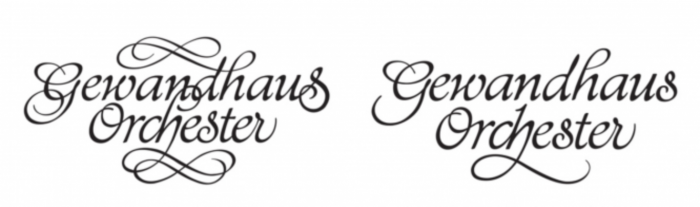
Gewandhausorchester: Logo-Redesign
... kannst du Beispiele der Fehler nennen?
ja freilich.
Aber ich bin überzeugt, daß nicht nur ich das kann. Das kann jeder, der etwas Ahnung von Schrift od. Kalligraphie hat. Es geht hier nicht um mich sondern um die Qualität einer wichtigen Arbeit. Deswegen jetzt hier ein etwas verwegener Vorschlag.
– Wer etwas konkretes zu dieser Kritik beisteuern möchte, lade die angehangene Datei herunter und drucke sie mit 100% auf A4 aus.
– mit Bleistift od. Farbstiften darauf die kritisierten Stellen markieren und benennen.
– den Kritikbogen dann fotografieren od. einscannen.
Dann wäre ein Vergleich der versch. Kritiken hier vermutlich sehr aufschlußreich. Das funktioniert aber nur, wenn wir uns auf einen gemeinsamen Zeitpunkt der Veröffentlichung einigen, damit wäre garantiert, daß jeder unbeeinflußt von anderen Meinungen seine Einschätzung abgibt.
hmm. dann würde aber sicherlich ein komplett anderer schriftzug dabei herauskommen. ich habe das redesign so verstanden, das der bestehende schriftzug nur vereinfach werden sollte, oder sind diese fehler in dem original nicht vorhanden?
Ich meine mit der Kritik nicht die Entscheidung(en) zur Vereinfachung/Veränderung des Zeichens. Solche Dinge sind legitim und auch immer subjektiv bewertbar. Nein, ich meine die handwerkliche Ausführung der Reinzeichnung, so wie sie jetzt vorliegt. Als wenn man den Entwurf so aber richtig machen würde.
… eignet sich das Foto nicht eher zum Pixelzählen als zur Beurteilung von Linien?
die Auflösung ist ausreichend.
Interessante Diskussion.
Ich glaube, dass gute Gestaltungsprozesse dialogisch verlaufen, egal ob sie mit einer Person oder mit vielen Personen geführt werden. Wichtig ist, dass man als Fachmann vom Kunden ernst genommen wird. Was für den Kunden aus Sicht des Fachmanns auch gelten muss. Ich finde die Herangehensweise des Büros ganz gut, stärkt es doch die Zusammengehörigkeit des Orchesters von innen. Grafische Ansätze, wie so etwas ausehen kann, gibt es viele und keiner ist womöglich unbedingt schlecht. Aber die Demokratie wurde in der Frage des Schriftzuges nicht wirklich ernst genommen, so mein Eindruck.
Ich mache häufig die Erfahrung, wenn ich mit einem Kunden gut in Kontakt gekommen bin, dass selbst der Laie in der Lage ist, mir als Gestalter zu Detailfragen gute Rückmeldungen zu geben. Außerdem sollte man die Strategie dieses Briefings nicht mit der Überarbeitung dieses besonderen Schriftzuges vermischen.
Die Überarbeitung ist bei genauerem Hinsehen aber tatsächlich ein trauriger Rest von Tschörtners Vorlage. So etwas hätte die Agentur an einen Fachmann abgeben sollen. Natürlich kann man einen solchen Schriftzug auch vereinfachen, aber eben nur mit kalligrafischer Erfahrung.
Nur neben bei zum Aspekt »Life-Layouting« zwei weitere Stimmen.
Aus zuverlässiger Quelle habe ich vorgestern die Einschätzung gehört, daß die Orchestermitglieder »das nicht ernst genommen haben und sich verschaukelt fühlten«.
Gestern kommentierte eine Kalligraphie-Kollegin: »Ganz schlimm finde ich diese Bejubelung des Prinzips "Live-Layouting"! Ich bin geneigt, dies mit dem früheren sog. Klofrauentest zu vergleichen, wo Hinz und Kunz bei Gestaltungsfragen mitentscheiden konnten.«
Wie gesagt, dies nur nebenbei. Ansonsten sollten wir uns hier weiter auf den Aspekt Überarbeitung des Tschörtner-Signets konzentrieren, wie angedacht. Denn das ist eine konkrete Materialisation grafischer Arbeit, der man auch legitim mit konkreter Kritik begegnen kann.
Dann bis demnächst, 12. 9., 12 Uhr.
Ich finde diese Diskussion schwierig und ich finde einen Ansatz im Sinne von »Finde die sechs Fehler im unteren Bild« stellt keine vernünftige, professionelle Kritik dar …
Richtig und Falsch scheint ja sogar in der Rechtschreibung schwer zu erklären zu sein, in der Mathematik kann man sagen 1+1=3 ist definitiv falsch, aber hier von klaren Fehlern zu sprechen finde ich etwas plump und macht den Eindruck von »Herr Lehrer, ich weiß was!«
So eine Gestaltung ist doch die Summe von Einzelfallentscheidungen, die nachher ein stimmiges Gesamtbild geben müssen. Wenn man sich einzelne »Fehler« oder Unstimmigkeiten herauspickt muss man auch an anderer Stelle eingreifen und schon kommt man vom Hundertsten ins Tausendste und es kommt ein ganz anderer Schriftzug heraus … Hätte man machen können – vielleicht auch machen sollen – das war aber nicht der Ansatz!
Manche Windung des alten Logos hatte buchstäblich die Funktion eines Mauerankers, manch andere diente der Gesamtbalance. Und wieder andere Formen hatten die Aufgabe, das Ganze als in sich harmonische, geschlossene Form zu vervollkommnen. Schaut man sich die modifizierte Nachfolgerversion an, so haben sich da gewisse Verschiebungen in der Gewichtung ergeben, die das Ganze luftiger, aber auch unruhiger wirken lassen. Die einst in sich ruhenden Schwünge wirken nun fast, als seien sie im Moment erstarrte Peitschenschläge. Das G wirkt, als rutsche es nach links weg und falle gleich um; das obere h, seines Gegengewichtsschnörkels beraubt, scheint unter der Last seiner Oberlänge in sich zusammenzusinken. Das geschrumpfte Schluss-s des Gewandhauses kann seine Aufgabe als Gegengewicht zum G nicht mehr erfüllen und lässt das ehrwürdige Gewandhaus auf der spitzen Oberlänge des Orchester-h in labilem Gleichgewicht hin- und herschwanken. So zumindest scheint es mir.  :-)